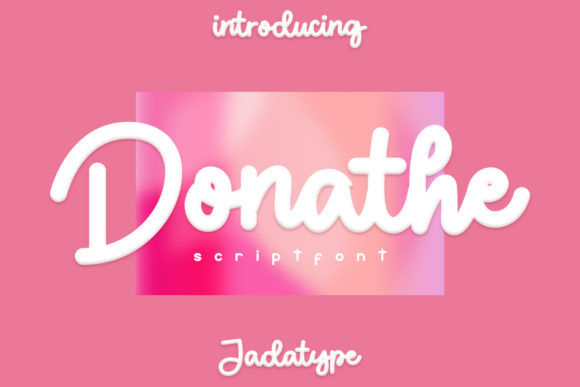
Донате - милый и скорописный шрифт, отшлифованный вручную.
Независимо от темы, этот шрифт будет невероятно полезным для библиотеки ваших шрифтов, так как он способен возвысить любое творение.